Trong thiết kế, font chữ là yếu tố then chốt tạo nên cảm xúc, cá tính và độ chuyên nghiệp cho sản phẩm. Tuy nhiên, để tìm được một kho font Việt hóa đầy đủ, đẹp, không lỗi, dễ dùng, lại còn miễn phí thì không hề đơn giản. Đó là lý do chúng tôi muốn gửi đến bạn kho font cực chất đã chọn lọc kỹ lưỡng, hỗ trợ đầy đủ tiếng Việt, phù hợp cho mọi nhu cầu thiết kế.
🎯 Font chữ có thực sự quan trọng đến vậy?
Câu trả lời là: Rất quan trọng.
Một thiết kế đẹp nhưng dùng font lỗi tiếng Việt, font không ăn nhập với nội dung, hoặc font quá phổ thông sẽ làm giảm sức mạnh truyền tải thông điệp. Ngược lại, chỉ cần chọn đúng font, thiết kế của bạn sẽ
➕ Thể hiện đúng cảm xúc và tone thương hiệu
➕ Tăng tính thẩm mỹ, sự chuyên nghiệp
➕ Dễ đọc, dễ tiếp cận và thu hút thị giác
➕ Gây ấn tượng mạnh mẽ với khách hàng
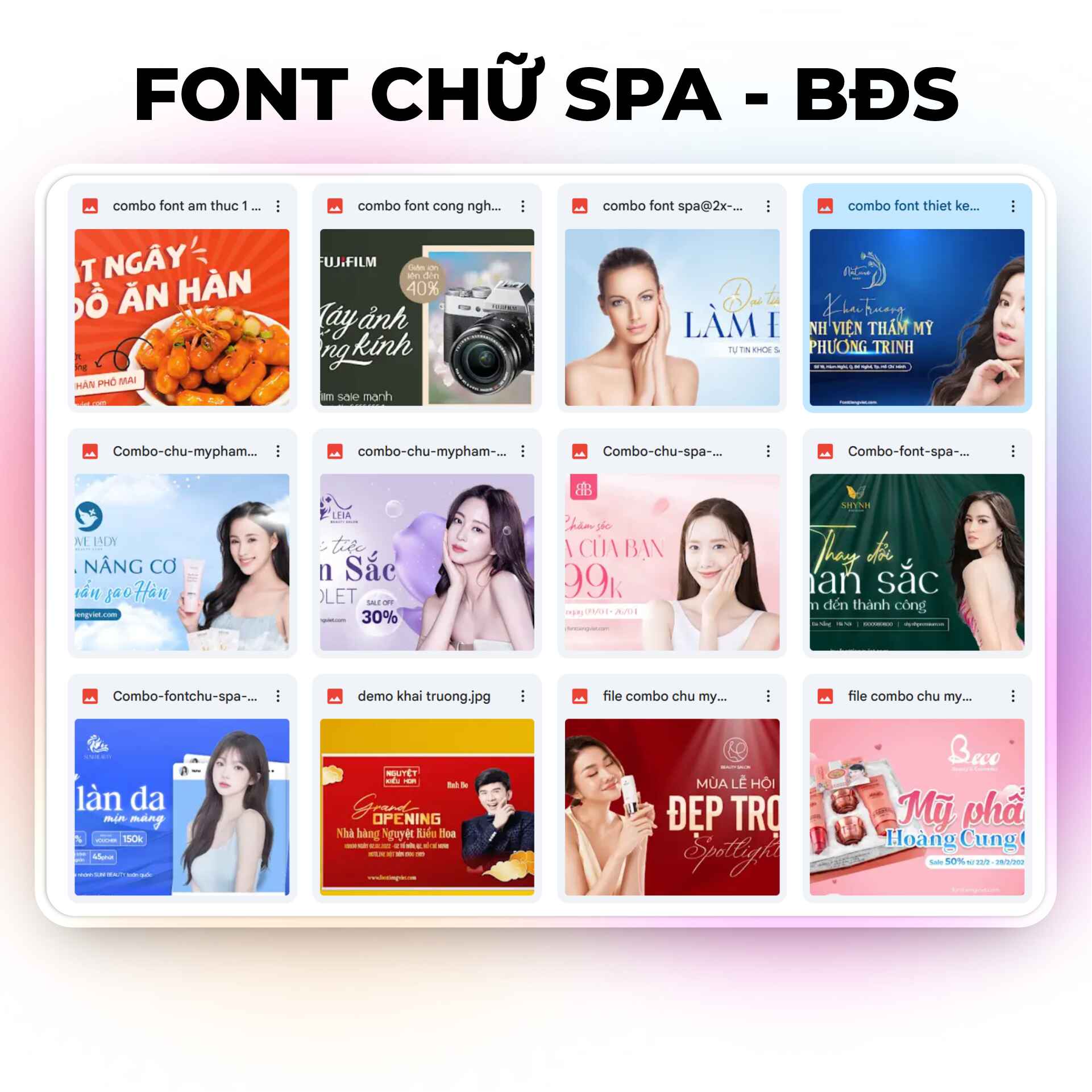
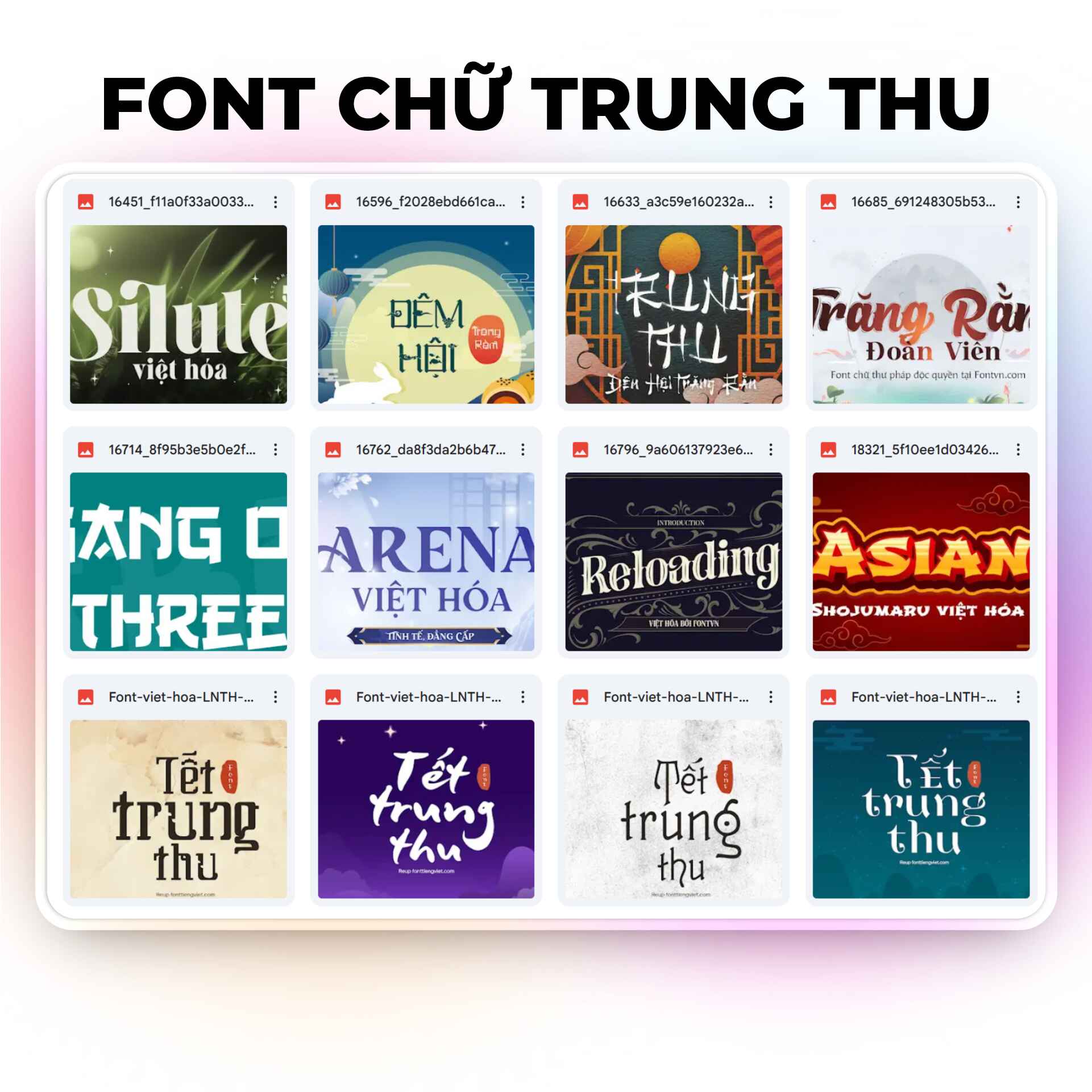
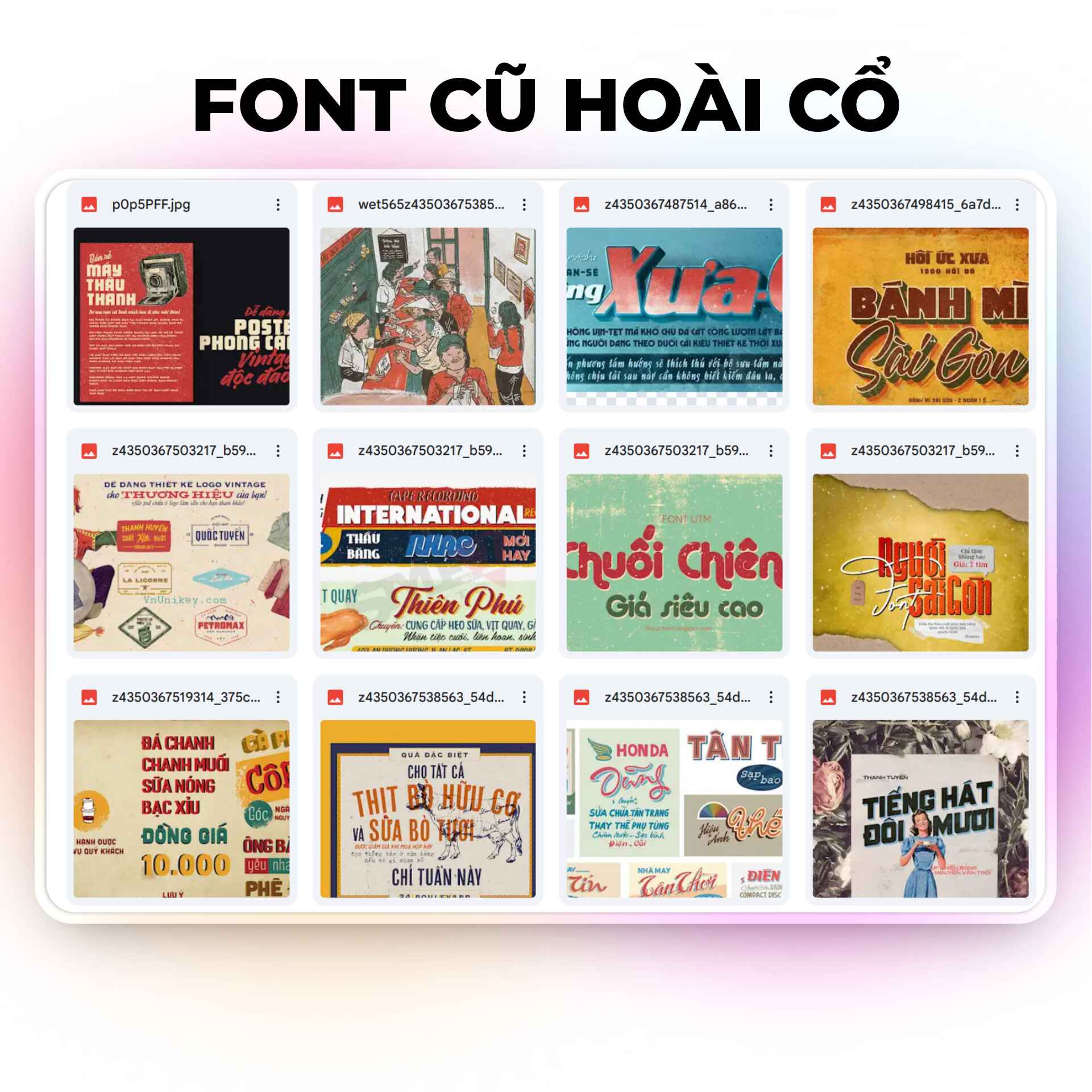
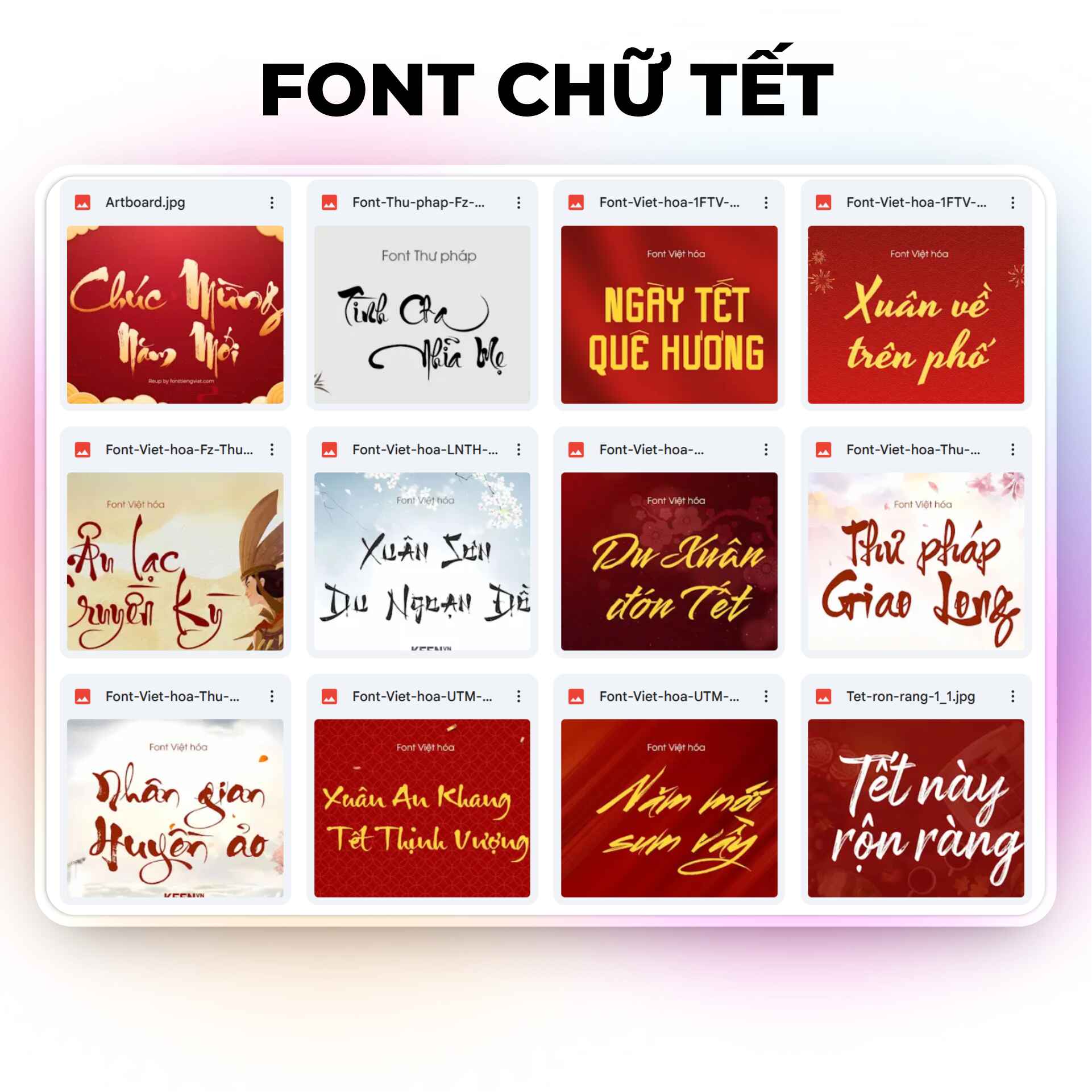
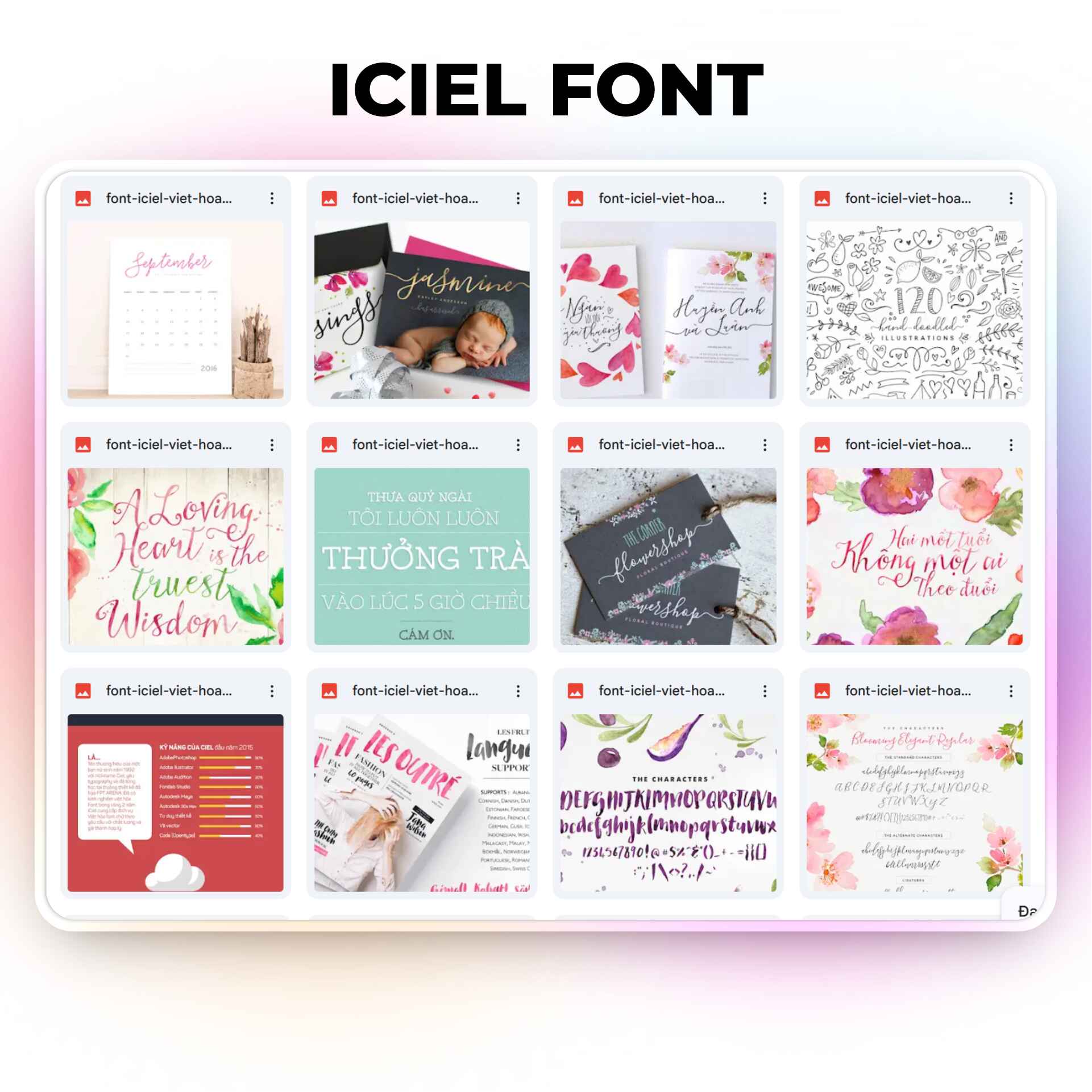
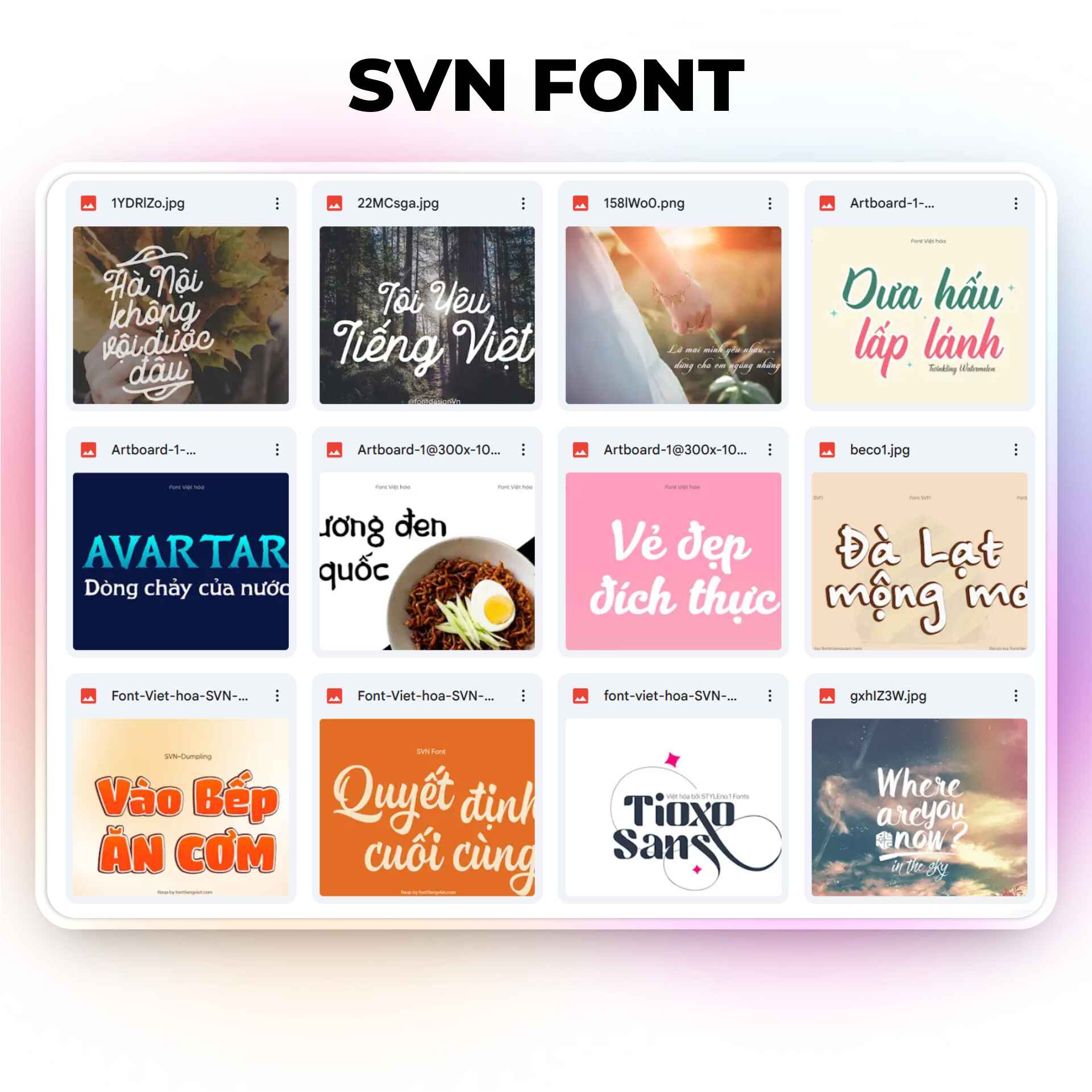
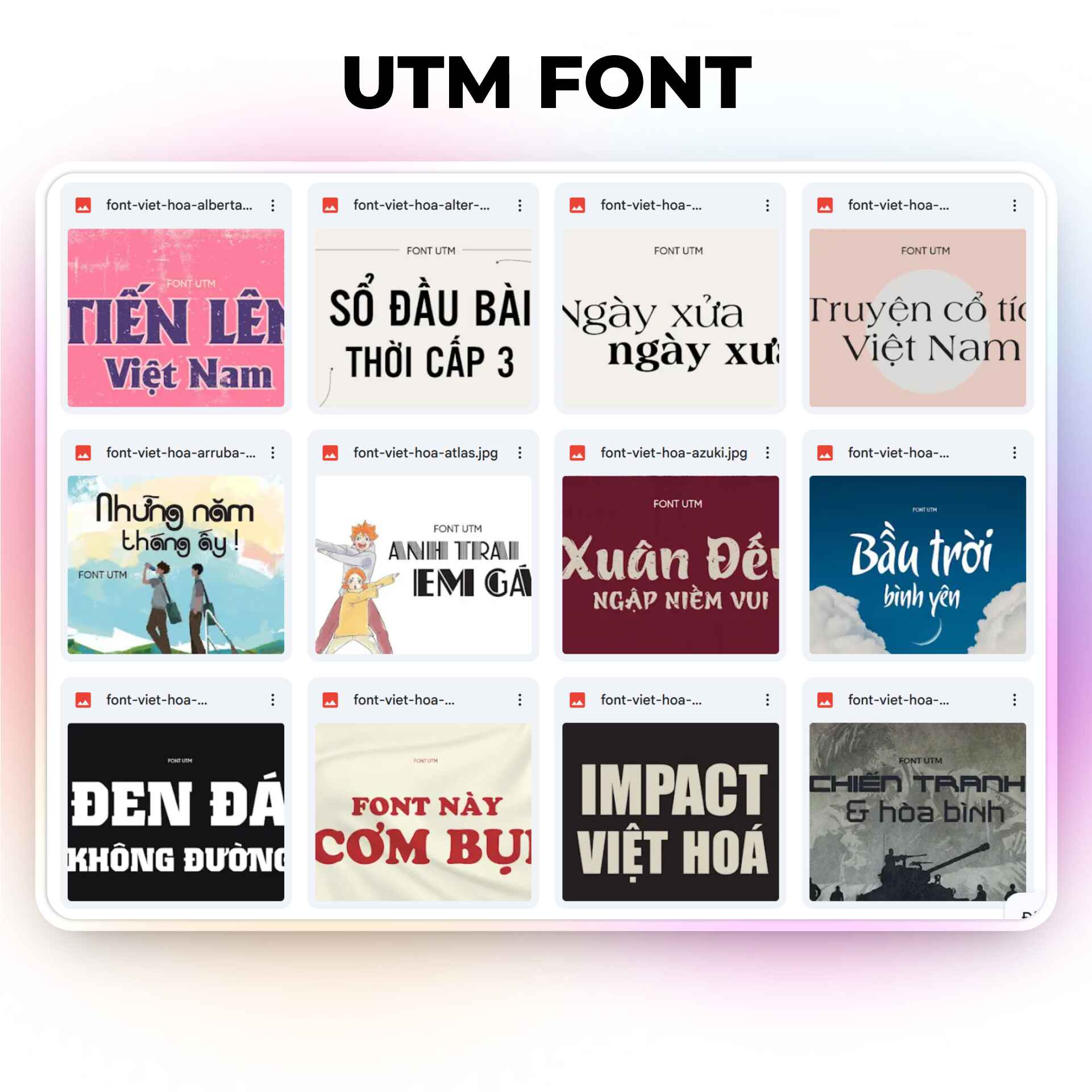
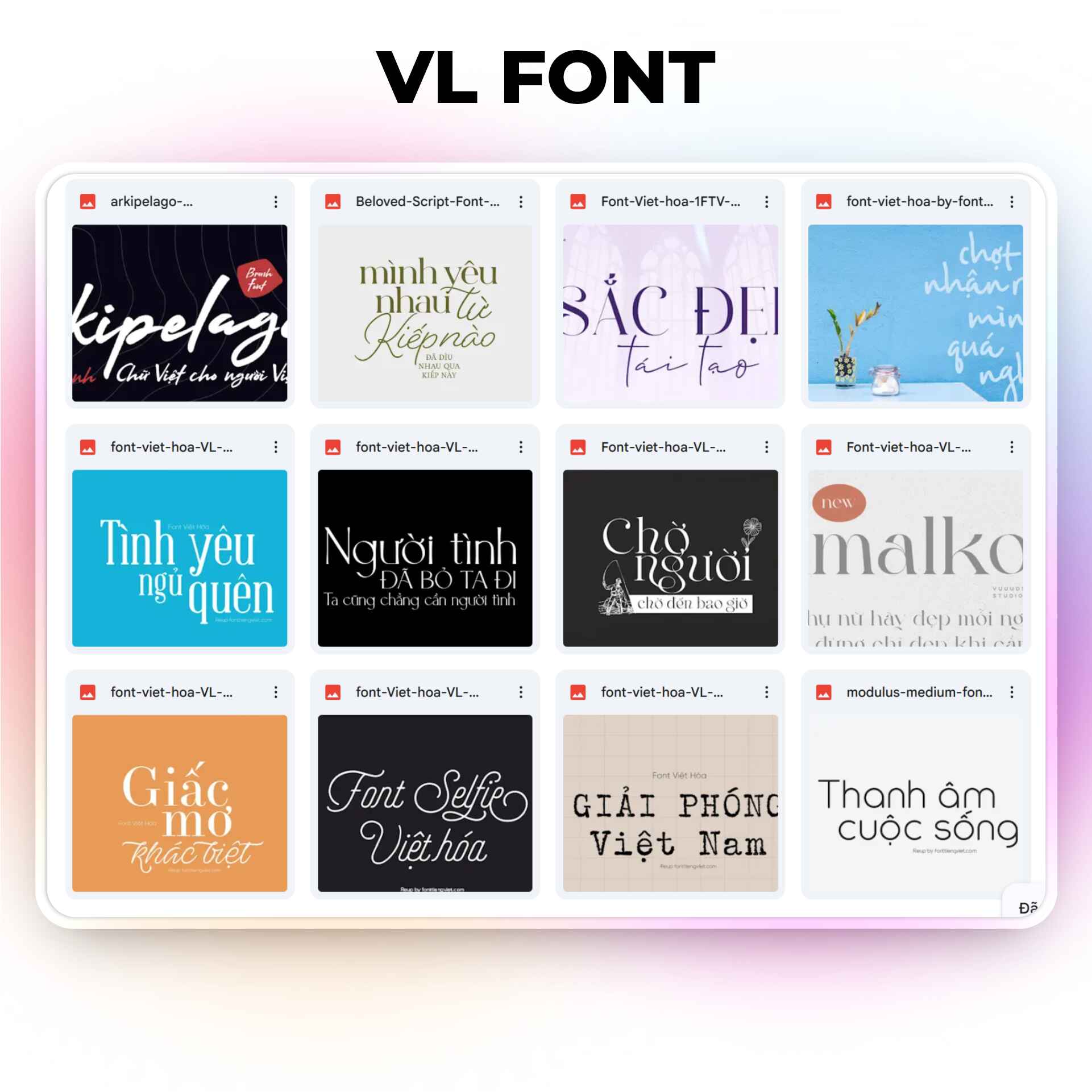
🔹 195 FONT UTM – Dễ dùng, tương thích cao
🔹 379 FONT SVN – Font chữ chuyên nghiệp, phổ biến trong in ấn
🔹 500+ FONT VL – Phong cách đa dạng, từ hiện đại đến cá tính
🔹 Full bộ Font ICIEL Việt Hóa – Nổi tiếng trong giới thiết kế
🔹 Font cho các dịp lễ: 2/9, 30/4, Trung thu, Giáng Sinh, Tết,…
🔹 Font cổ điển – Retro – Vintage
🔹 Font làm Vlog, Video Caption, YouTube Thumbnail
🔹 Tổng hợp Top font chữ đẹp được designer dùng nhiều nhất
🔹 Top font chữ phổ biến nhất trên Google Fonts
🔹 Mẹo kết hợp font chữ cho thiết kế không bao giờ bị "phèn"